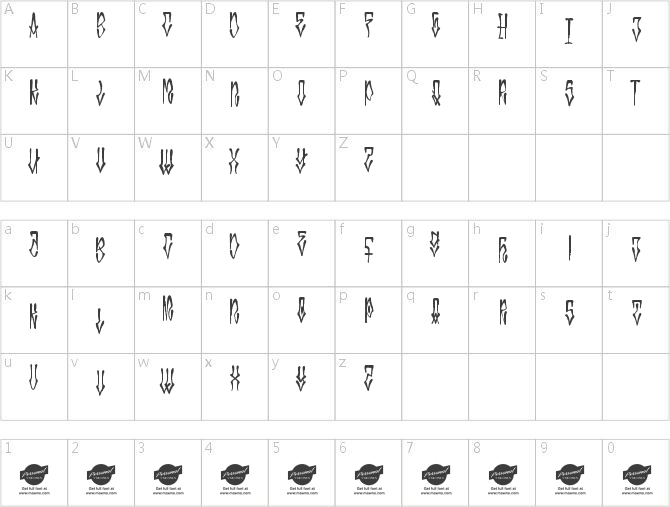
Monsta-Tag-Personal 詳情頁
Monsta-Tag-Personal字體字庫是一款讓人賞心悅目、百看不厭的英文字體,適合各類廣告和產(chǎn)品包裝設(shè)計(jì)應(yīng)用,字體大小0.48MB,格式為ttf字體,上傳用戶是哼哼哈兮,作者/版權(quán)方為未知